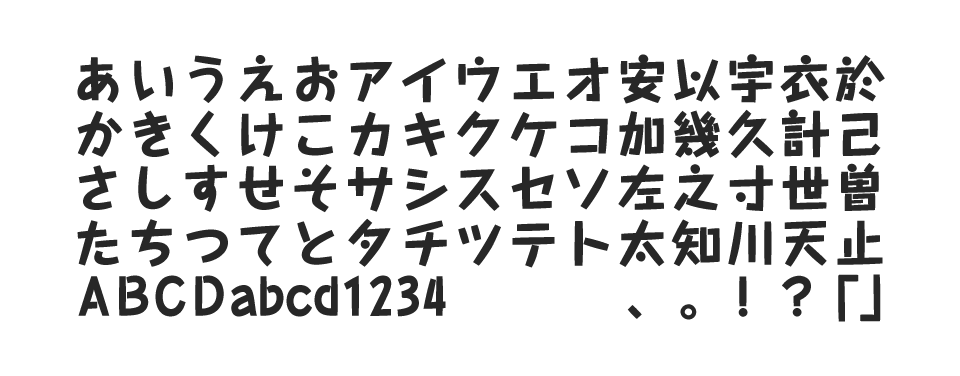
タカハンド H | 書体見本 | モリサワのフォント
「タカハンド」は、ふくらみのあるストロークとドットのエレメントが特徴の、個性的なフリーハンドスタイルの書体です。おとぎ話の中から抜け出してきたようなほのぼのとした温かさと、手書きをイメージさせる小気味よいリズムがあり、語りかけてくるような息...
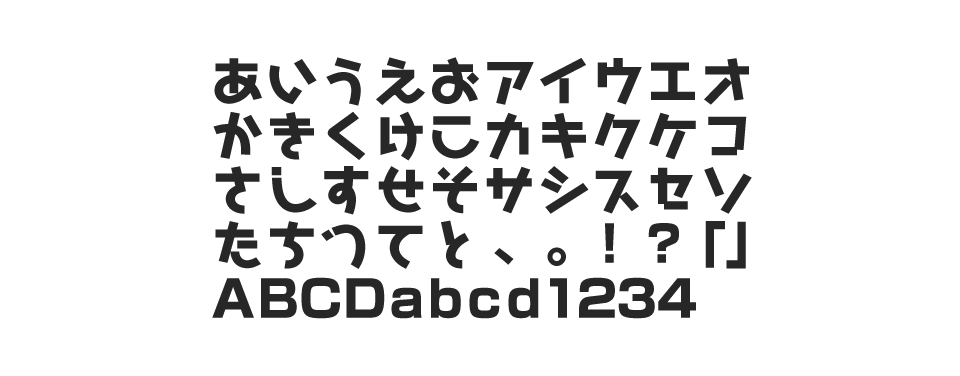
はせトッポ H | 書体見本 | モリサワのフォント
手書きのニュアンスが楽しい「はせトッポ」は、ユニークでカジュアルなゴシックかな書体です。直線と丸文字風のカーブやループの組み合わせに、濁点などのデザインがリズミカルなアクセントとなって、軽やかでかわいらしいイメージの文字組みを実現します。「...
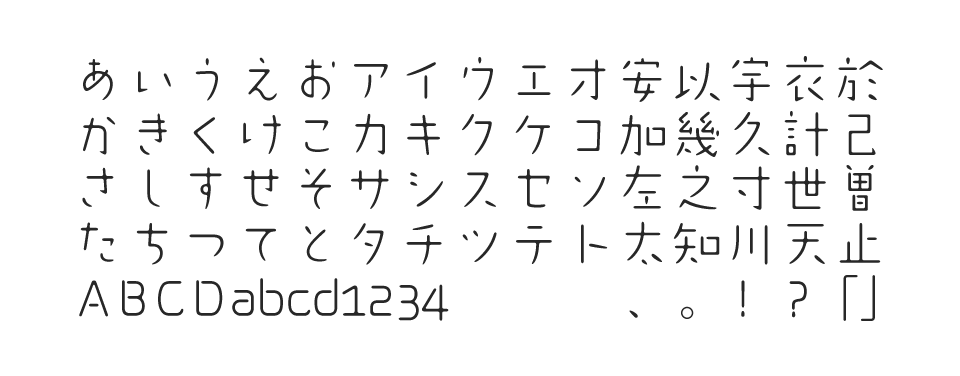
はるひ学園 | 書体見本 | モリサワのフォント
「はるひ学園」は、素朴なかわいらしさとデザイン的な楽しさをもつオリジナル書体です。先端や内角を丸く処理した直線的なロゴ風のエレメントで構成されていますが、パラパラとした飾り気のないストロークと余白を活かした独特の骨格が、現代の空気感といった...
A1明朝 | 書体見本 | モリサワのフォント
「A1明朝」は、モリサワ最初期から長く愛されているオールドスタイルの明朝体です。漢字のゆったりとしたカーブと、かなの優美な表情が生み出す独特の味わいが特徴です。デジタル書体化にあたって、画線の交差部分に写植特有の墨だまりを再現するなどし、や...